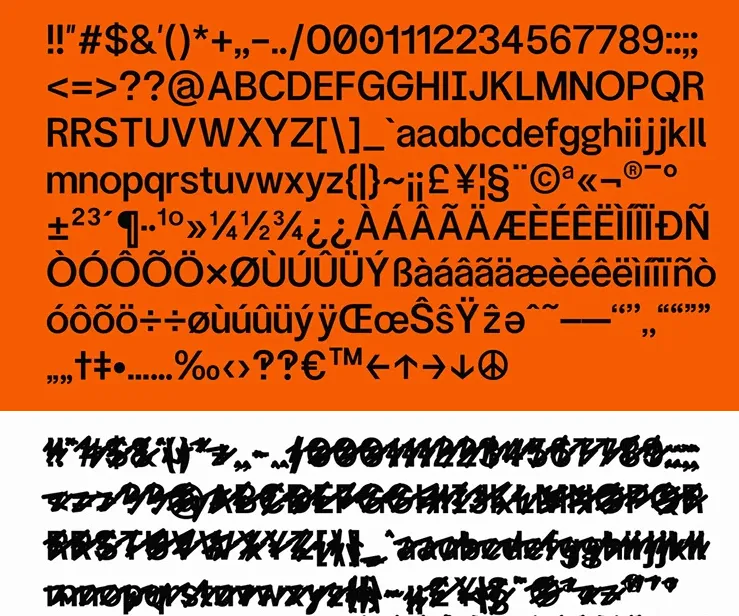
Free Font „Sans Control“: Normal + durchgestrichen
Gabriele Servolini und Jasmine Micheli haben mit „Sans Control“ einen neuen, kostenlosen Font entworfen. Das besondere an der klassischen serifenlosen Schrift ist aber der durchgestrichene Schriftschnitt. Dieser erinnert an einen Textmarker, mit dem die Buchstaben durchgestrichen oder übermalt wurden. Die Schrift gibt es kostenlos und frei zur Nutzung und Bearbeitung bei pixelsurplus.com, man muss sie aber in den Warenkorb legen und den (kostenlosen) Einkauf durchführen.